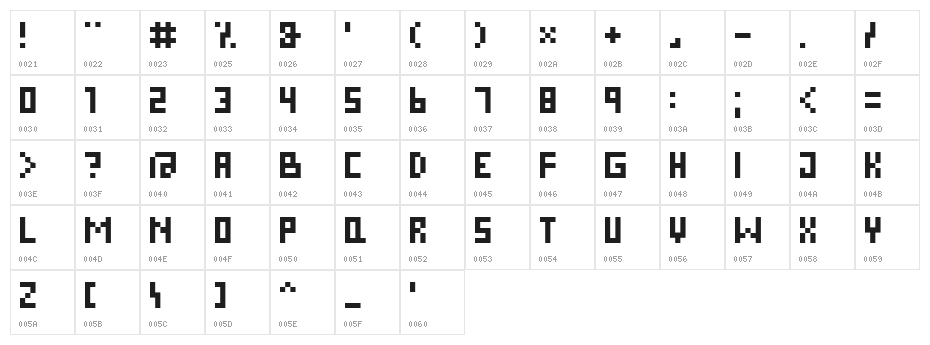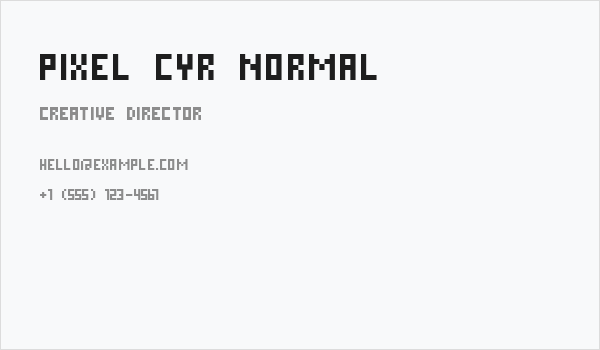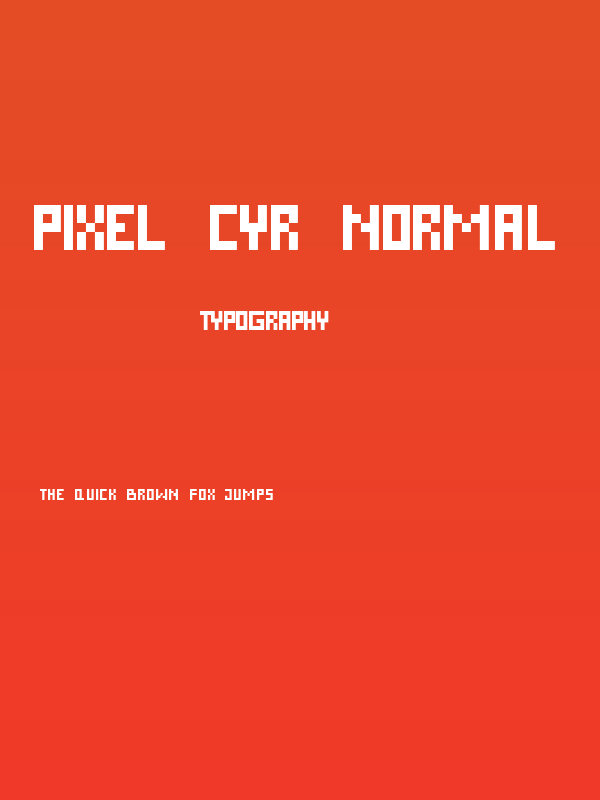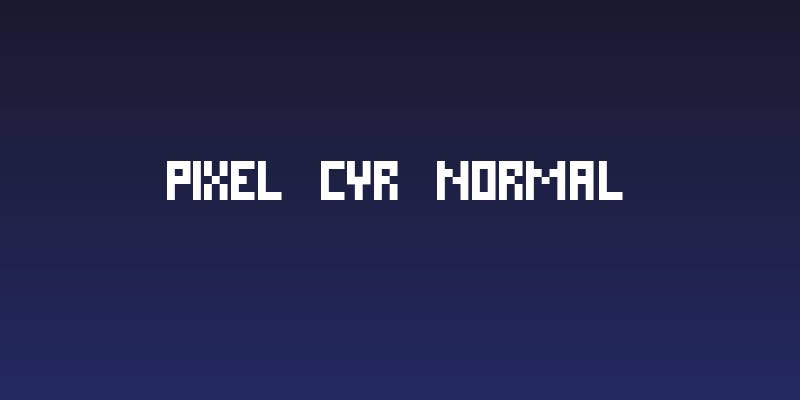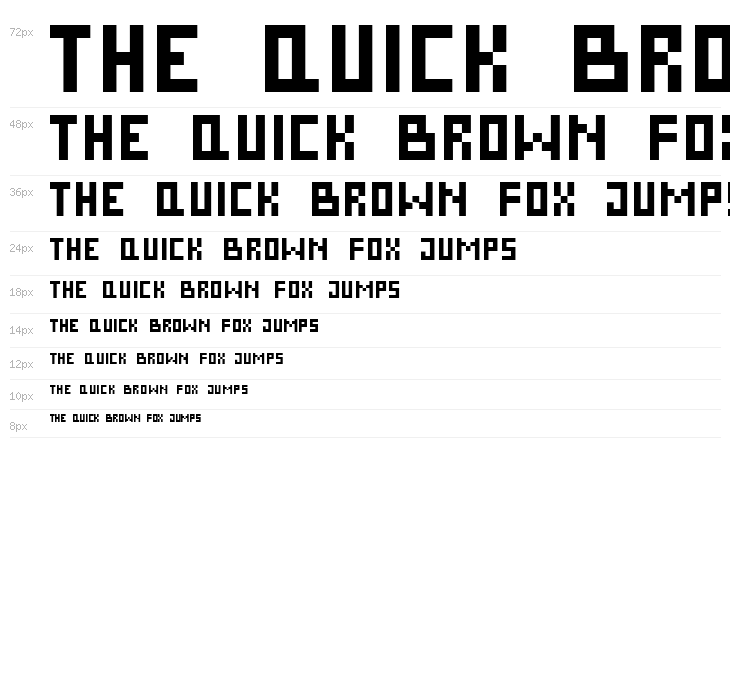
Pixel Cyr Normal Font
| Nume | Pixel Cyr Normal |
| Greutate | Normal |
| Versiune | Version 2.0; 2002; initial release |
| Categorii | Pixel |
| Stil general | Retro, Digital |
| Caz de utilizare | Headlines, Logos, Digital displays |
| Proiecte propuse | Ideal for retro-themed video games, digital art projects, and any design work that seeks to evoke a sense of nostalgia for early computing or gaming eras. |